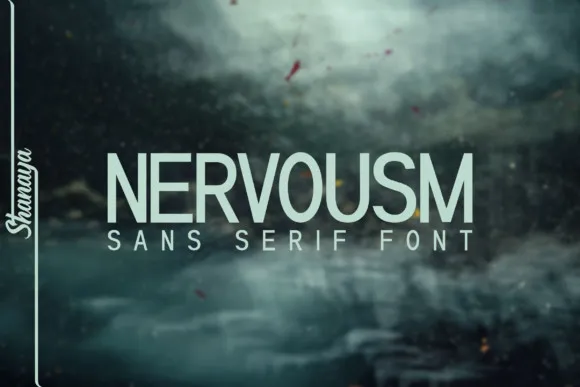
Aqui está uma descrição em português para a página de download da font ‘Nervousm Sans Serif Font Demo’, baseada no material original: Bem-vindos! Nossa fonte moderna e clean, Nervousm Sans Serif, é perfeita para ambientes limpos e elegantes. É uma tipografia sem serif que combina elementos simpáticos de um estilo clássico condensado. O designer Shanaya Creative criou esta fonte pura, que traz a beleza e sofisticação do design moderno aos textos mais simples. Nervousm é perfeito para uso em aplicações profissionais ou quando você quer dar uma cara única à sua marca. Além disso, Nervousm também se adapta com facilidade para diferentes contextos – seja no design de logotipos, impressão de cartões de convite, revistas ou até mesmo para a criação de sites. É uma fonte versátil que vai do texto clássico à tipografia moderna, sendo ideal tanto para textos menores quanto para se destacar em grandes espaços visuais. Nervousm é um verdadeiro complemento para ambientes que valorizam design simples e sofisticado. Ele é perfeito para criar uma identidade visual única e elegante, seja você criando um site personalizado ou querendo imprimir cartões de visita com um toque único. Sem dúvida, ele se encaixa em qualquer aplicação onde a estética do texto importa. Experimente Nervousm hoje e transforme o modo como você usa textos digitais!